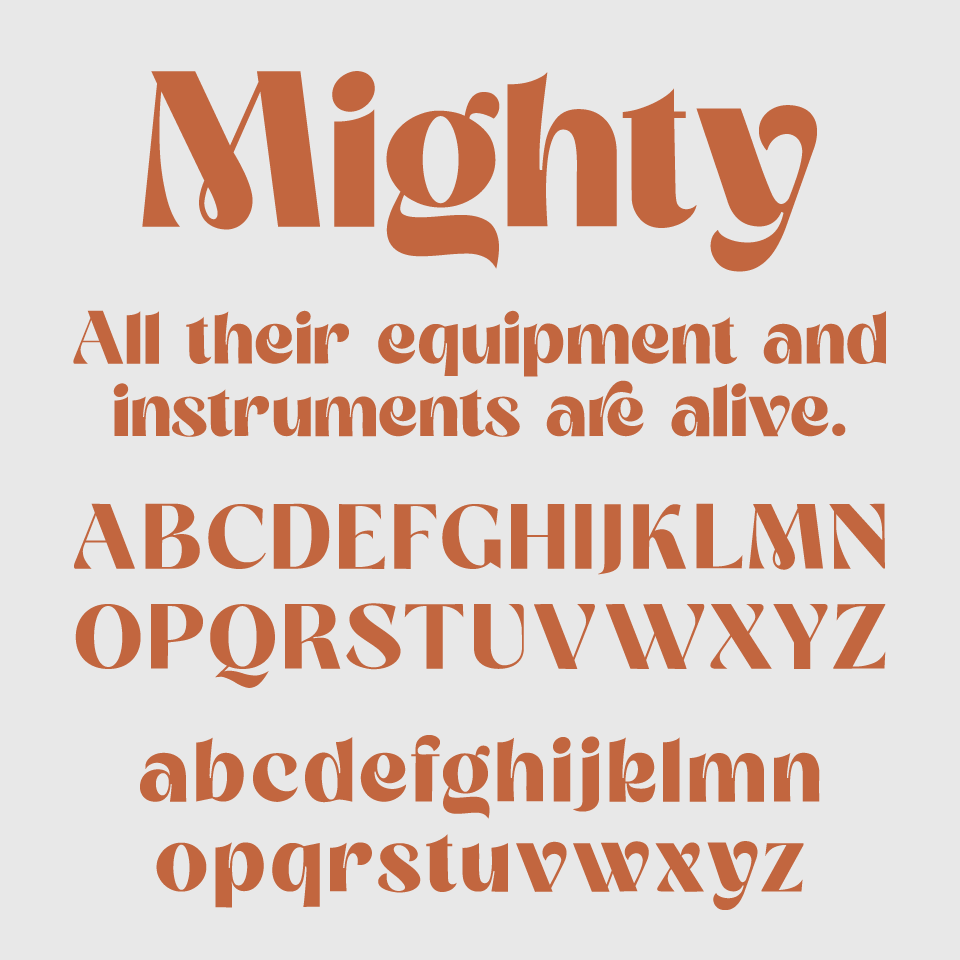
Mighty Marineフォントは、しなやかなカーブと鋭く伸びたエッジが共存した、ファッション性の高いディスプレイフォントです。
文字の一部に入った装飾的なひねりが目を引き、まるで風になびくような遊び心を取り入れているデザインが素敵です。
上品さと大胆さをあわせ持つデザインで、モード系のビジュアルや、アート感のある誌面にぴったりなフォントです。タイトルに使えば、静かな強さを漂わせる存在感を演出してくれます。